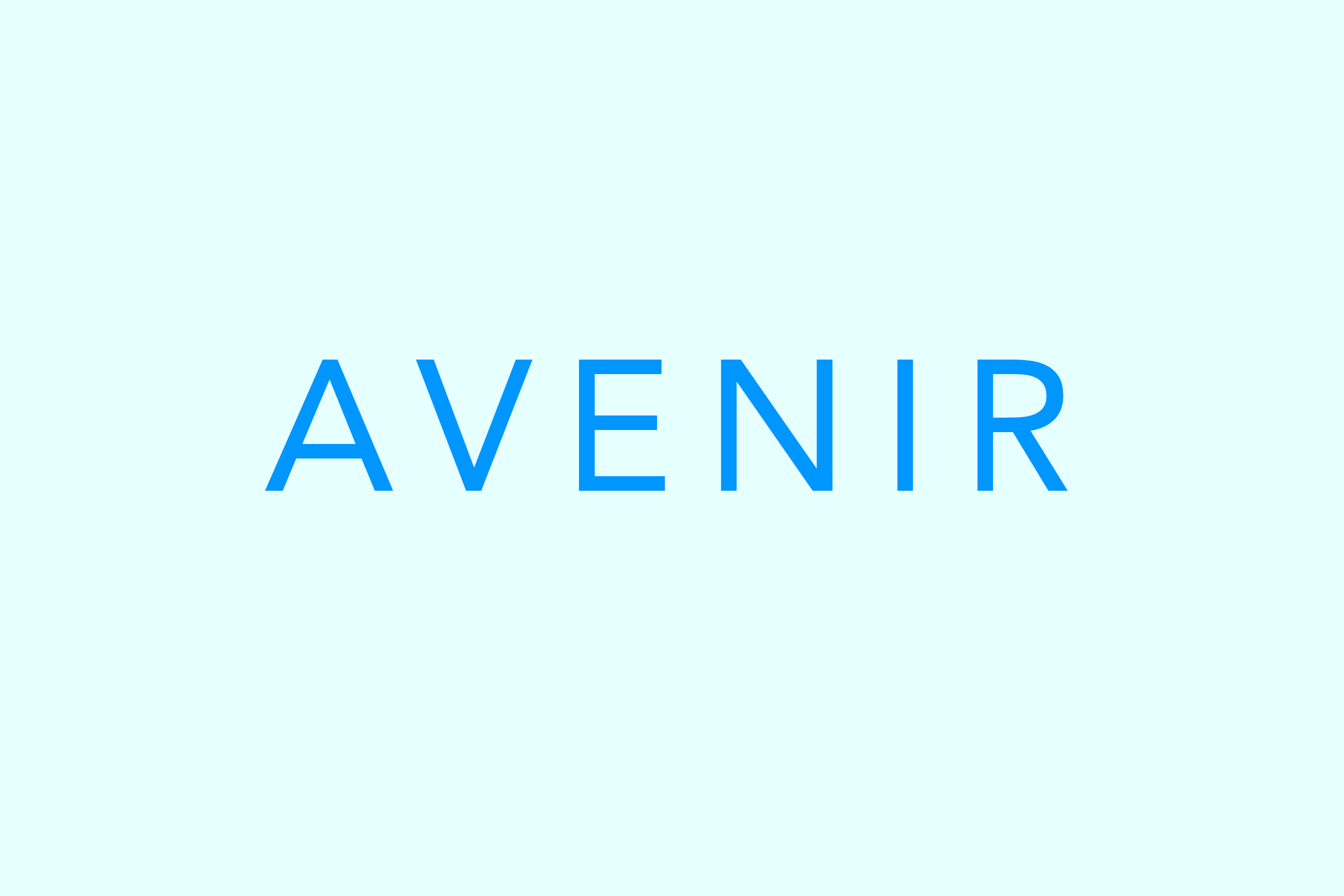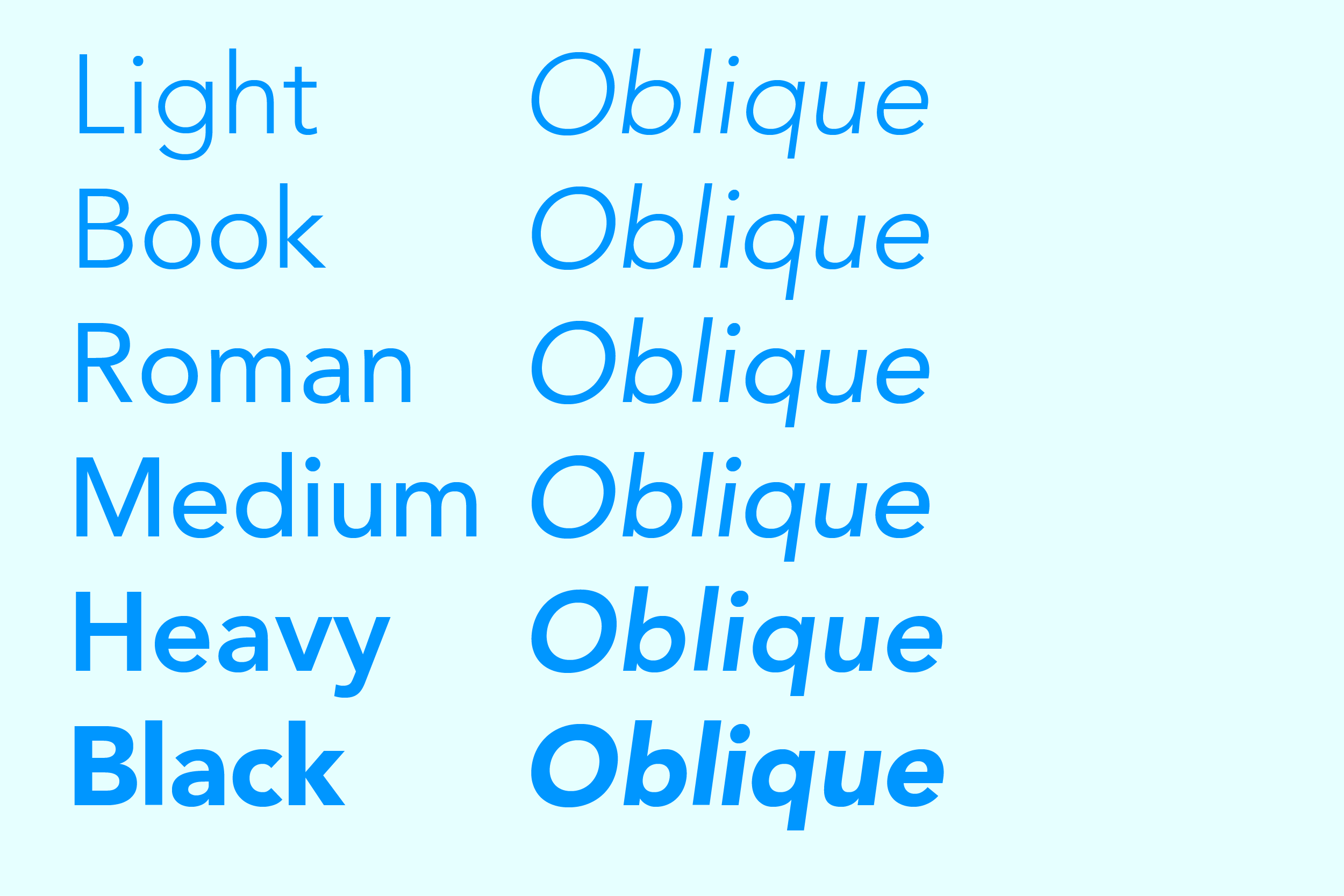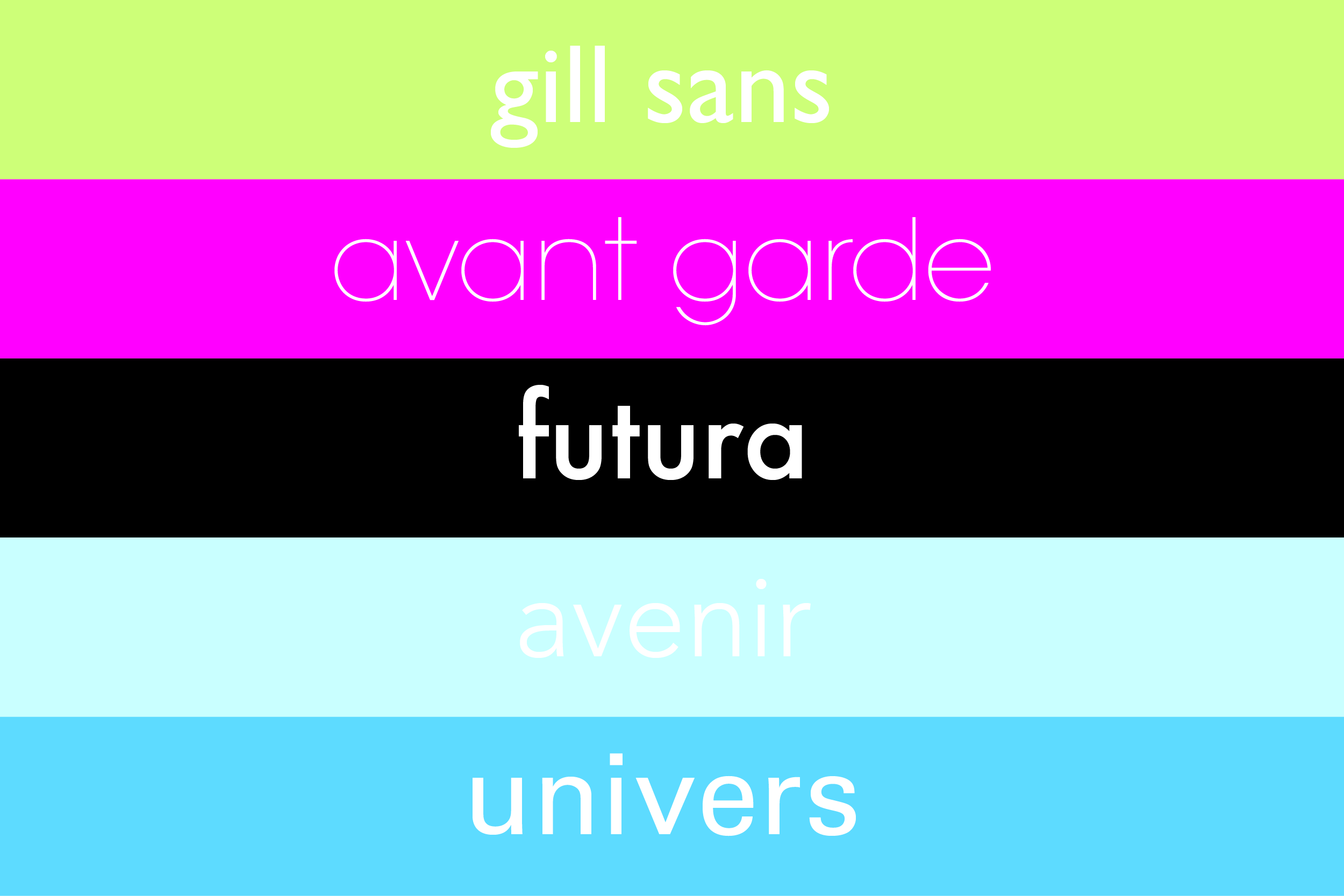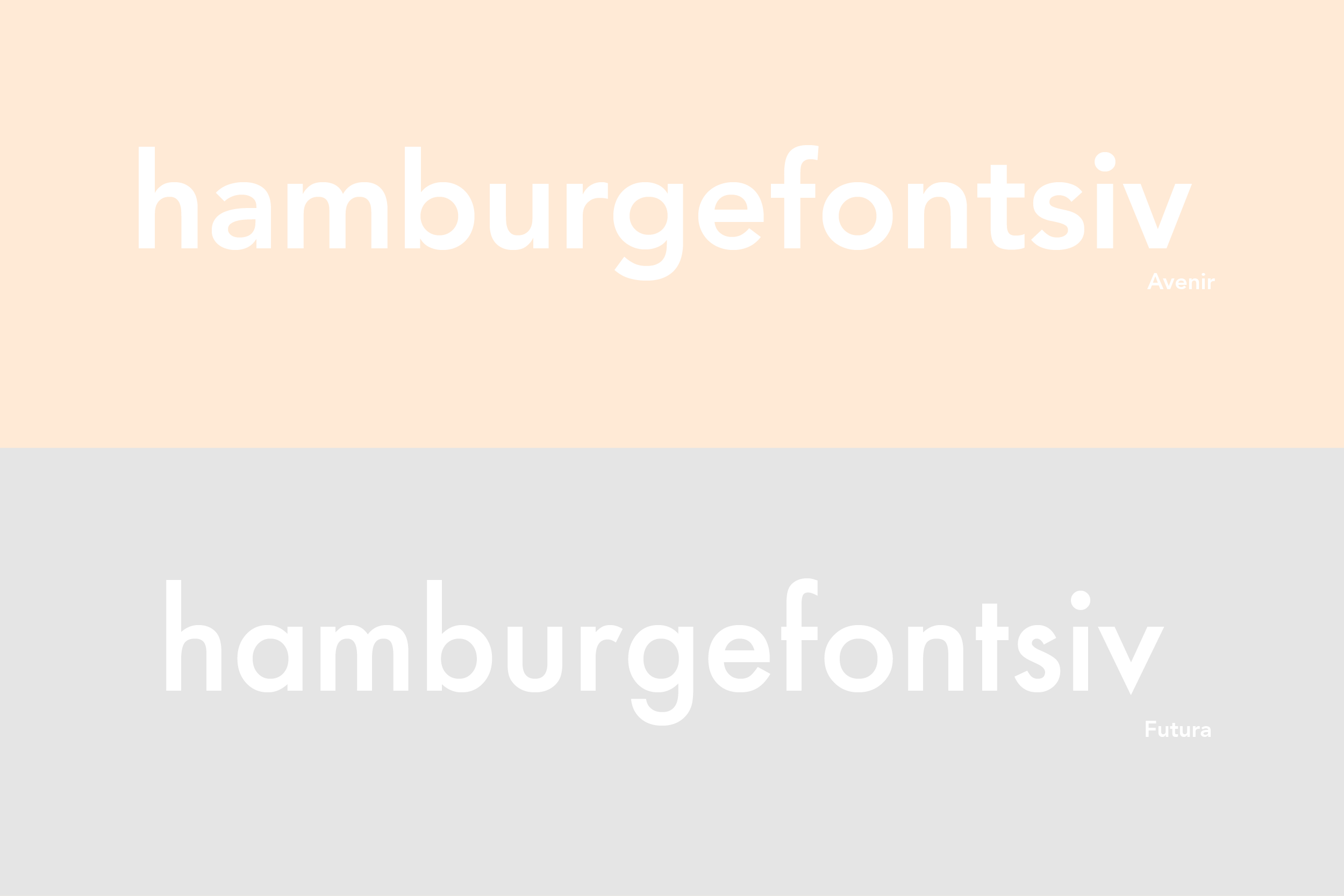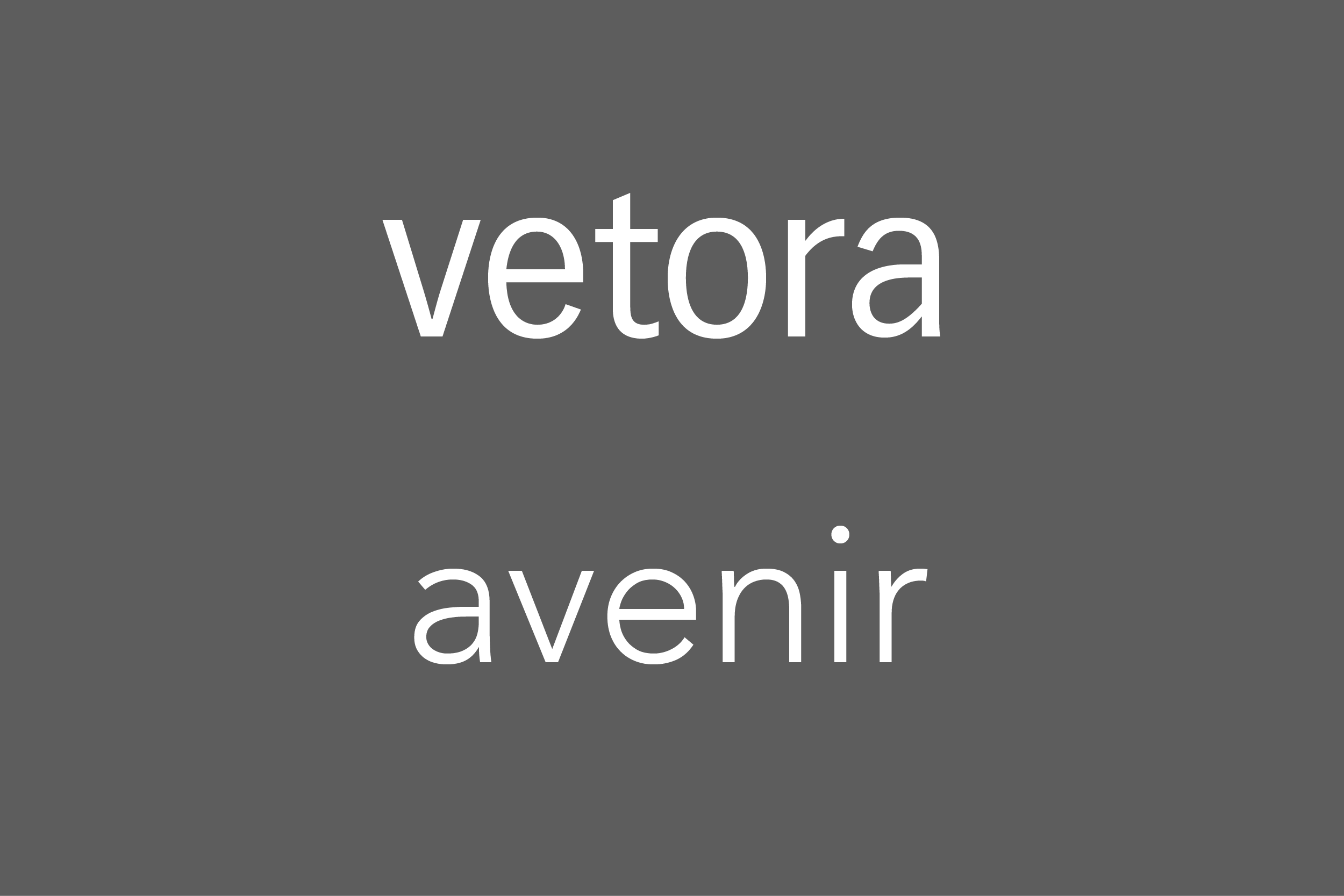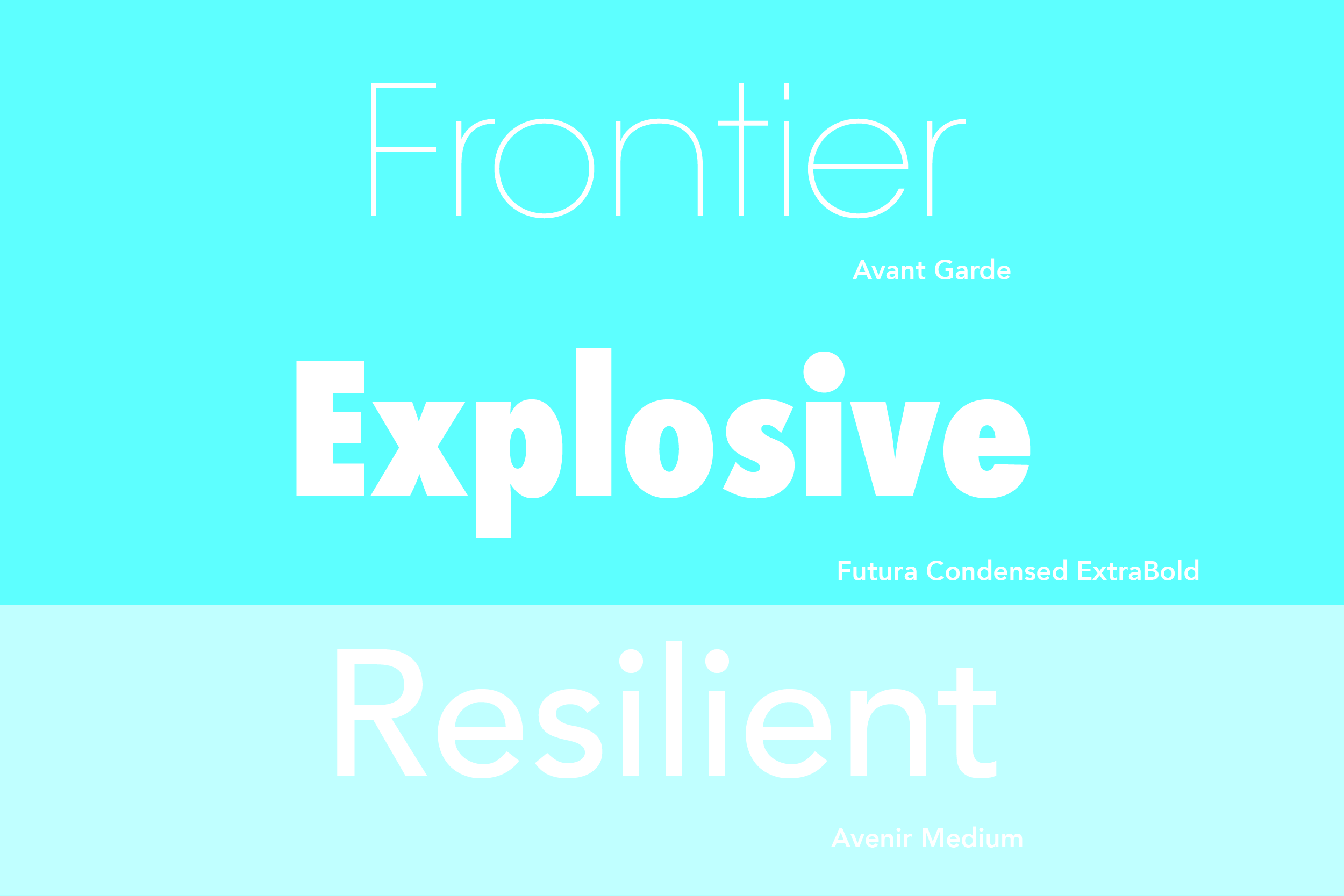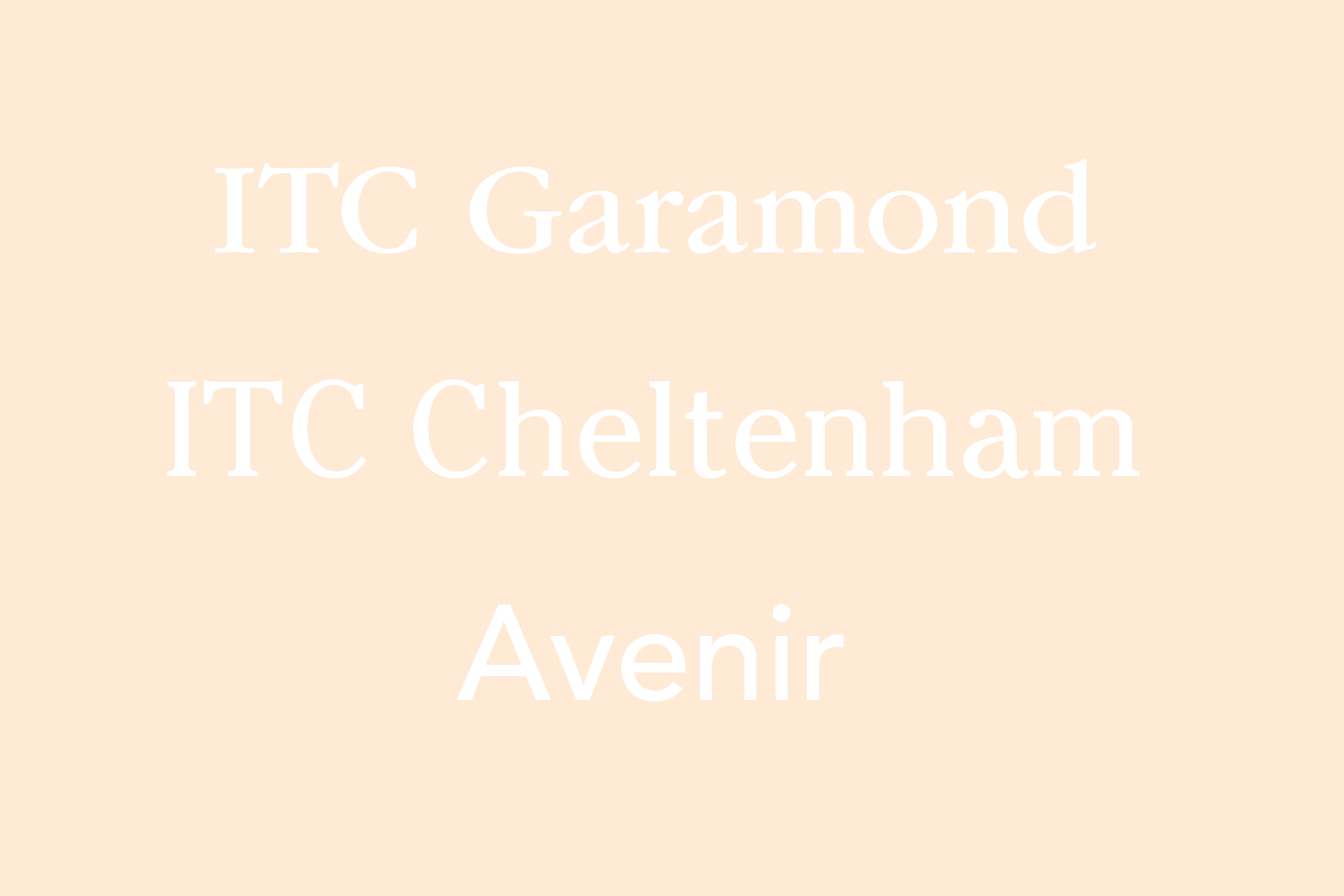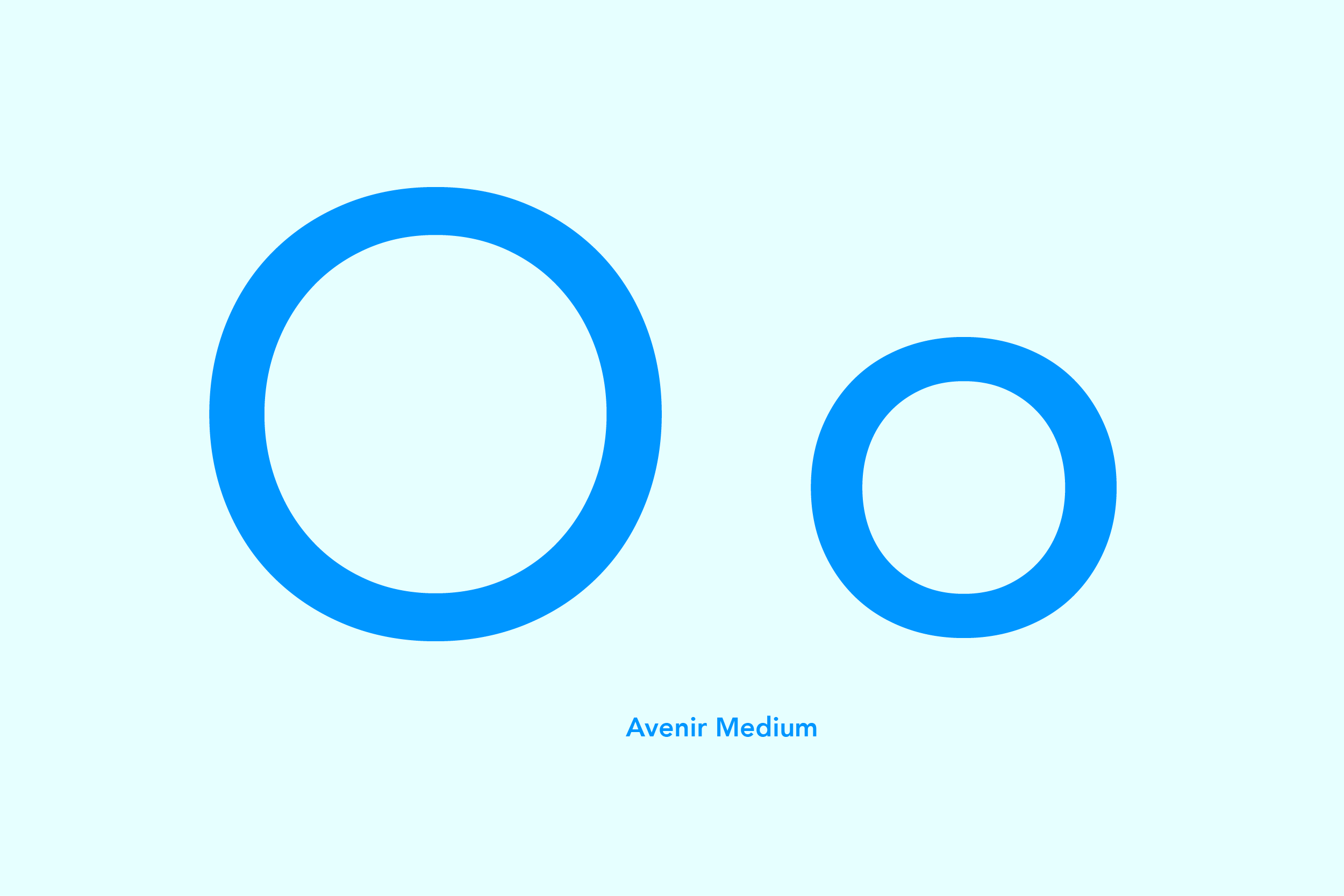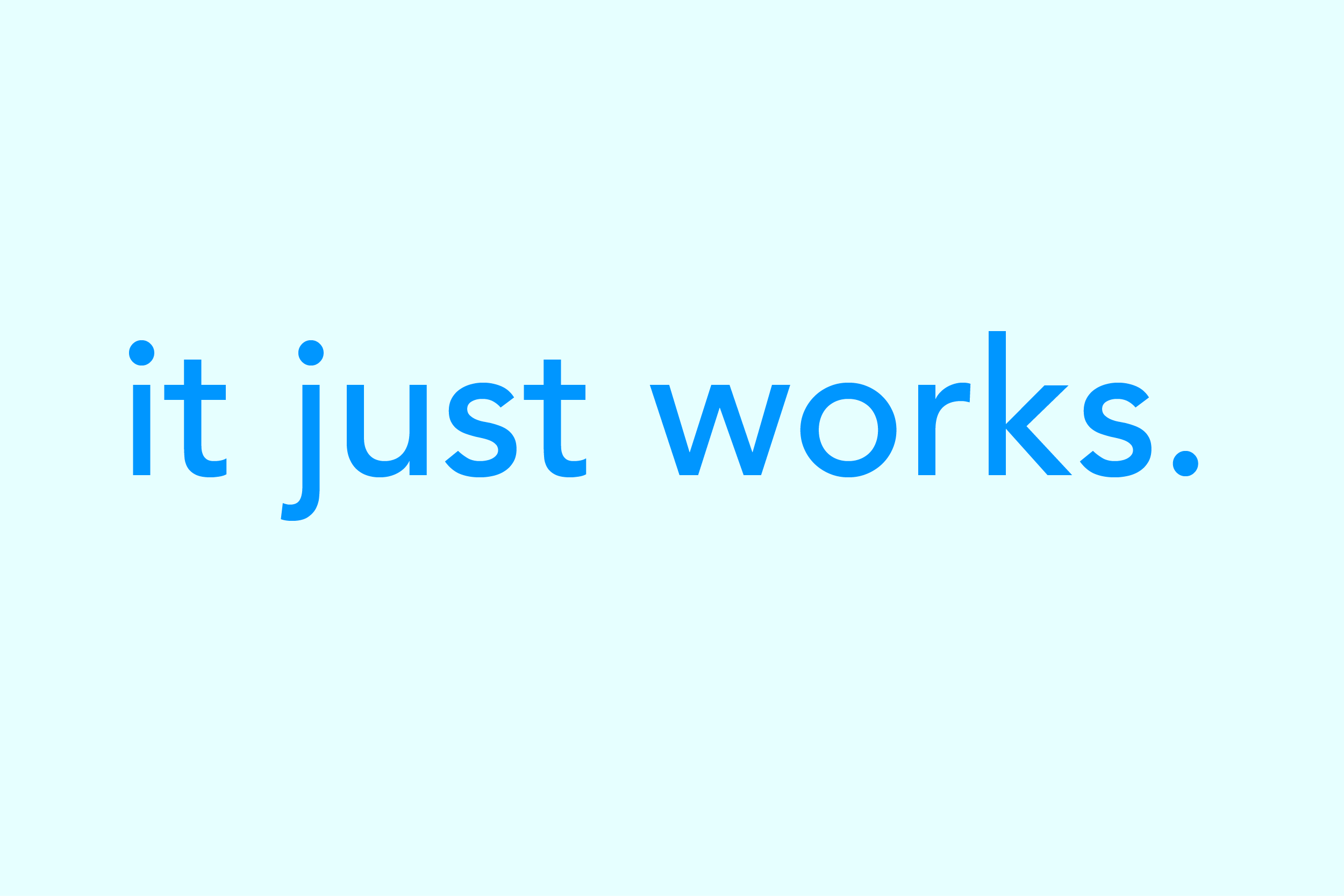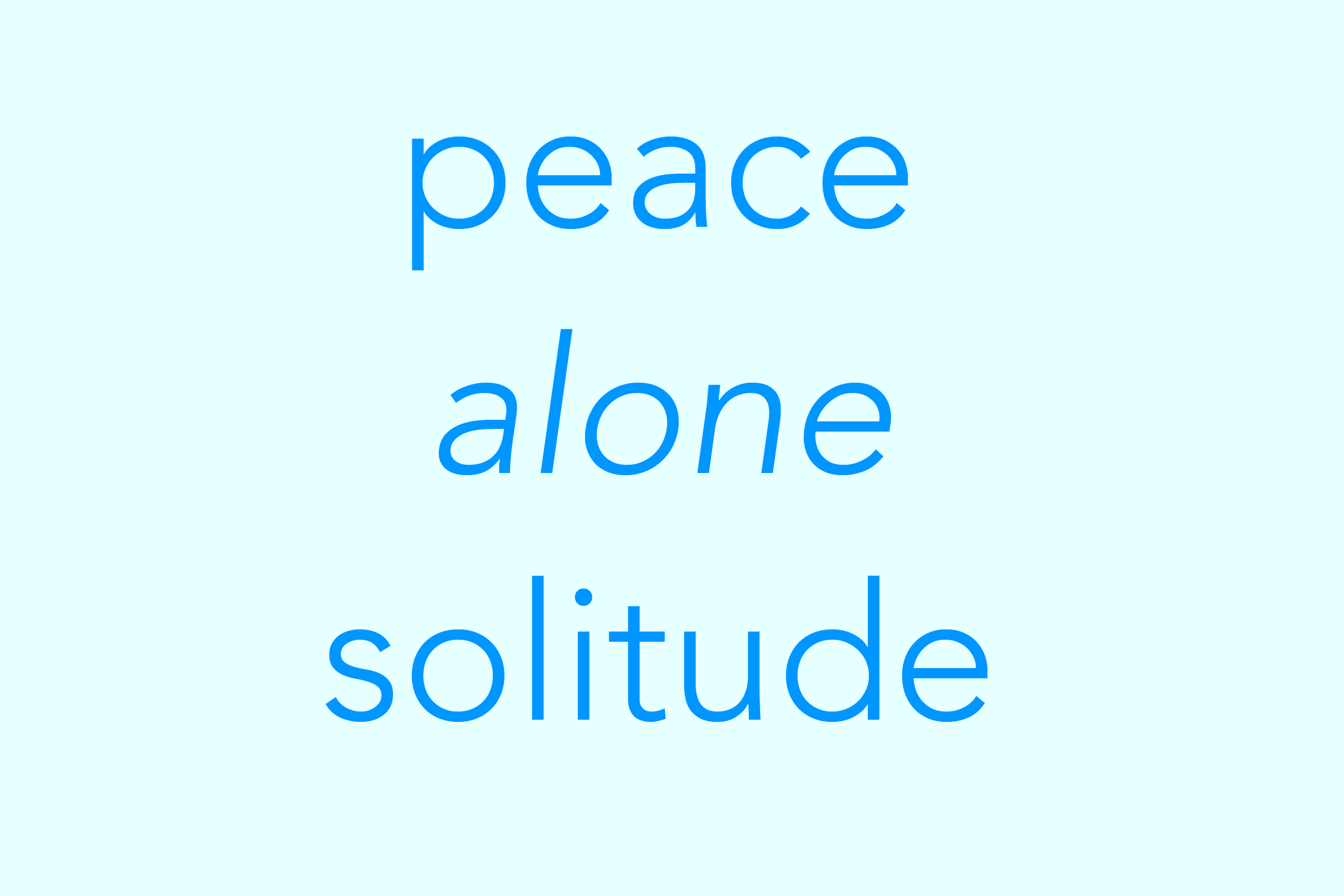
Avenir:设计土壤变化与字体风格复兴
日本设计大师原研哉在他的名著《设计中的设计》和《欲望的教育》说道「必须让设计土壤肥淆,好设计才得以健康生长」,感觉这比喻放诸字体设计也同样准确。
1988 年推出的 Avenir,是西文字体设计大师 Adrian Frutiger 最引以自豪的作品。刚推出时,在 Frutiger 先生坚持下,Avenir 一直只有六个「直立」(Upright)字重。直到 1989 推出 PostScript 电脑字型版本,才一次多加六个斜体(Oblique 1)字重,成为一个有六字重十二款式的字体家族。
从《Adrian Frutiger Typefaces. The Complete Works》一书中得知,Frutiger 先生设计 Avenir 并没有特别原因的,只是大概在八十年代中期,他综观自己多年设计生涯,作品堆中就欠缺了一套像 Futura、Avant Garde 类的「几何无衬线体」(geometric sans serif)作品,也直觉这将是市场的未来。所以,他花大量时间研究 Futura、Avant Garde、Gill Sans 2 等一类字体家族的设计特性、优点与缺点,并开始试作一套带几何风格的字体家族。
一路下来,Frutiger 先生发觉自己并不想要设计一套「新 Futura」。反之,他将一般几何无衬线体的冷酷观觉完全改过来,变成感觉人性化、又有点可爱的 Avenir。
可是推出后,Avenir 并没有很受欢迎,价值远远被低估,跟 Vectora 一类作品一样,永远被 Univers、Frutiger 等经典设计的光茫所掩盖。即使 Frutiger 先生刻意以「Avenir」(法语未来的意思)寄望新设计能够与「Futura」(拉丁语未来的意思)一竞高下,这想法也可惜始终没能够实现。
回看八十年代,那是个人电脑科技爆炸性发展的年代。苹果、微软、Adobe 相继兴起,其中 PostScript 科技的发明、扩展,完全改变字体设计的面貌。这时候人们追求新颖、冲击性的美感,Avant Garde、Futura ExtraBold Condensed 一类高调、性格鲜明的字体在欧美是广告行销常客;即使喜好历史感,也是投向 ITC Cheltenham、ITC Garamond 一类字体。 Frutiger 先生的眼光有误,那时候的市场虽然喜好几何衬线体,却不认受人文风(即使六十年代末 Hans Eduard Meier 的作品 Syntax 曾经带起过人文热潮),划时代的作品放在未成熟的设计土壤上,始终不会发芽。
Frutiger 先生也说到,Avenir「O」的造型,是他多年字体设计经验的集中表现,是他工艺的最高峰作品,有着「just works」的吸引力。在设计 Avenir 时,他总是孤独一人、处于安心平稳的状态,没有助手帮忙、以一人之力完成。 Avenir 的表情就是他本人性格。最终,Avenir 尘封多年,中间的日子除了个别欧洲国家、如荷兰爱用 Avenir 外(荷兰是十分喜爱 Frutiger 先生设计的国家),始终难以兴起。
三十年后,Hoefler & Co. 著名字体 Gotham 在美国总统奥巴马总统选举宣传中大红—— X-height 大、上延、下延短,人性化、有点可爱的小草字母,大草略宽、重心偏低的设计特色,一时间成为大众喜爱的字型,「泛滥成灾」。而 Avenir 重新在你我眼中出现,则是它作为 Starbucks 咖啡厅内广告,作为 Gotham 的替代品,这大概是 2008、2009 年的时候。
转眼间三十年,我们中间经历过资讯爆炸、互联网兴起,脑袋每天被塞满资讯的年代,现在世人反希望每天能够觅得一丝安静安宁,追求 a peace of mind。特别是最近五、六年,金融海啸,将人们依靠金钱建立的荣耀、繁华一下子卷走;「311 地震」几近将日本东北催毁,东京竟成为受辐射污染威胁的城市,我们曾经以为固若金汤的人类文明、原来是多么脆弱。我们心灵受到伤害了,要停一停,想一想,反思人类生命的价值、文明的价值。设计的土壤随着这大环境变化,也有着深刻的改变。
Avenir Medium 的「小确幸」感,竟慢慢得到大众认同——在 Dribbble 看到 iOS apps 的试作画面由 Helvetica 换成 Avenir,多么可爱、生气勃勃,温婉;AirBNB 大量运用 Avenir medium,那介乎粗与不粗之间的尴尬感,多么贴近 Kinfolk 式的生活态度。
最近,Avenir、Avenir Next 随 OS X 系统附载,一步当上主角。笔者喜欢 Avenir「a」的温婉、「g」的可爱、「s」的人性美,Avenir 三十年前所带出的舒适气氛,竟反映这一世代的时代精神。
喔?文章要完了?未来会如何呢?天知晓,我们也身在当中喔。